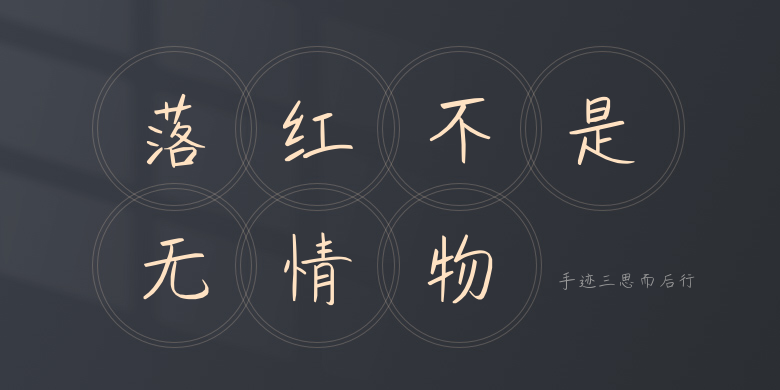
手迹三思而后行
手迹三思而后行,这款字体结构工整、笔画清晰,兼顾美观与易读性,适用于标题、正文、海报、包装、LOGO 等多种场景。字形优雅稳定,风格百搭耐看,适配日常排版与创意设计,让文字呈现更舒适、更具质感。手迹三思而后行一笔一画,皆是细节,以均衡的比例、流畅的线条打造舒适视觉体验,字形端正大气,风格简约现代。无论是商业设计、品牌宣传还是日常排版,都能轻松驾驭,让文字更有格调与力量。手迹三思而后行字体下载。